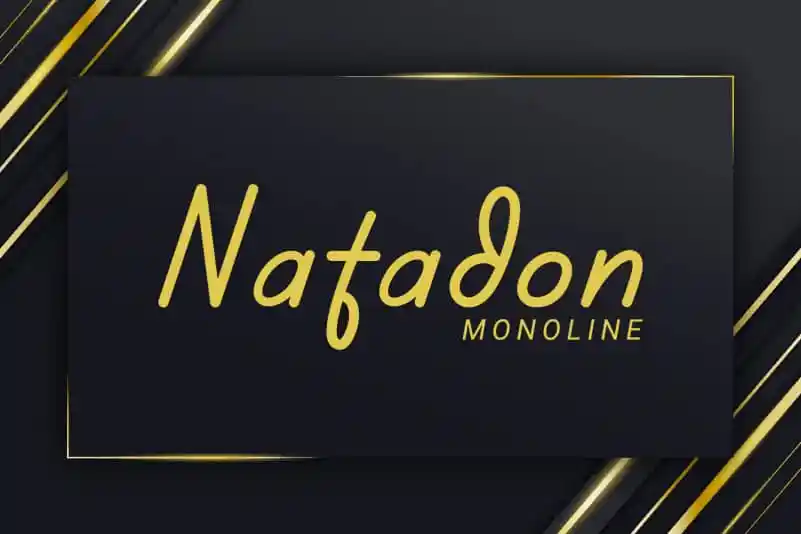
Natadon Handwritten Font – Download Grátis
A Natadon Handwritten Font é uma fonte escrita a mão que traz consigo um toque delicado e autêntico. Ideal para quem busca uma mistura de elegância casual em seus projetos de design, ela se destaca como o elemento perfeito para personalizar diversas categorias. Seja você criando cartões de convidados assinados com estilo próprio, criando materiais de marca única ou produzindo selos para celebrar grandes momentos, a Natadon Handwritten Font trará sua identidade pessoal e singularidade ao seu trabalho. Suas linhas fluidas e personalizadas complementam design variados – do branding e logotipos aos anúncios de wedding designs e até mesmo as assinaturas dos usuários finais. Esta fonte escrita a mão é o atalho perfeito para quem deseja incorporar um toque humano em seus projetos digitais, elevando-os ao nível mais alto de sofisticação e originalidade.
Designer: Jprint Studio